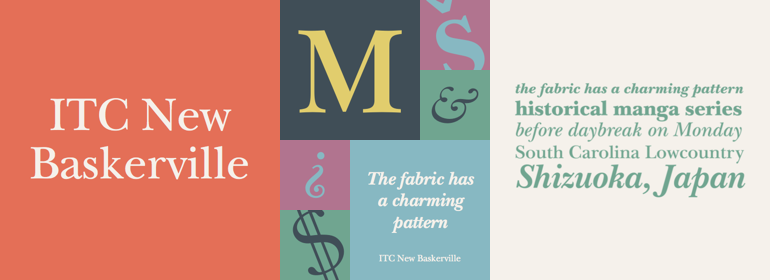
ITC New Baskerville®
ITC New Baskerville®,这款字体结构工整、笔画清晰,兼顾美观与易读性,适用于标题、正文、海报、包装、LOGO 等多种场景。字形优雅稳定,风格百搭耐看,适配日常排版与创意设计,让文字呈现更舒适、更具质感。ITC New Baskerville®一笔一画,皆是细节,以均衡的比例、流畅的线条打造舒适视觉体验,字形端正大气,风格简约现代。无论是商业设计、品牌宣传还是日常排版,都能轻松驾驭,让文字更有格调与力量。ITC New Baskerville®字体下载。
字体品牌: ITC(Monotype) 设计师:Quaranda,John 字体分类:衬线体、正文字体 字体属性:外文 字符集:Unicode 发布时间: 2018